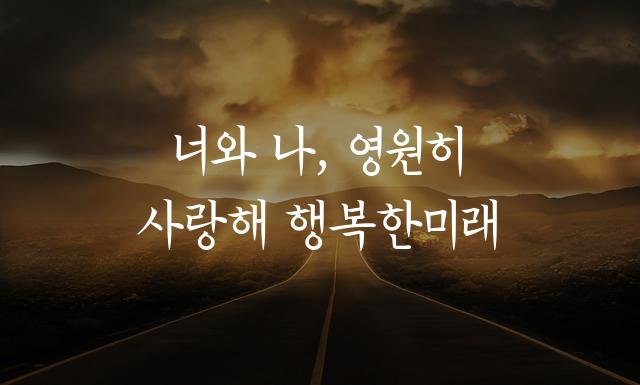
한글재민체는 붓글씨와 고전체의 조화를 통해 옛날 한글의 미를 현대에 재현한 폰트입니다. 따뜻하고 정감 있는 손글씨 바탕이 특징입니다.
한글재민체은(는)
바탕 스타일, 손글씨, 명조/전통, 레트로, 펜/붓터치, 감성적인, 복고풍 계열의 생김새를 가지고 있으며
교육 자료, 어린이 책, 보고서/문서 등에서 자주 활용되며, 효과적인 메시지 전달에 적합합니다.
이 폰트는 교육, 크리에이티브, 유아/가족 분야에 잘 어울리며,
친근한, 편안한, 단순한 느낌을 담고 있는 것이 특징입니다.